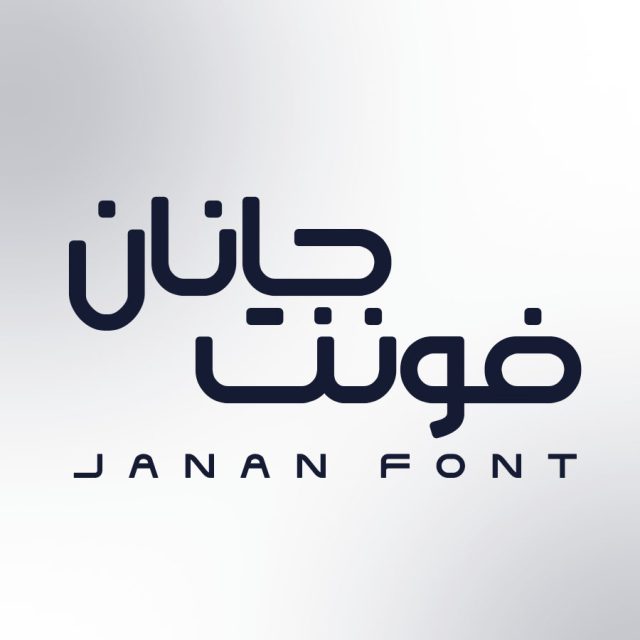
فونت فارسی جانان Janan Font
فونت حرفه ای جانان منتشر شد!
بهترین فونت برای طراحی لوگو و تولید محتوای فارسی
جانان مرکب از جان و آن ریشه در جان دارد… یک نفس بی یاد جانان برنمی آید مرا! فونت فانتزی جانان اثر جدید هاشم شهرزاد یک فونت مدرن و دارای طراحی زیباست. تایپ فیس جانان برای کلمات و عبارات کوتاه و بلند طراحی شده و بیشتر مناسب کاور و اسلاید شبکههای اجتماعی و تبلیغات و بسته بندی میباشد. از آنجایی که فونتهای فانتزی امروزه بسیار محبوب هستند، از فونت جانان میتوانید برای طراحی لوگوتایپ و موارد دیگر استفاده کنید.
فونت تایپوگرافی جانان
طراحی لوگو و تایپوگرافی با فونت
- طراحی بسته بندی و چاپ
- مناسب استفاده در تابلو ها
- مناسب استفاده در تبلیغات محیطی
- فونت برای طراحی لوگو
- مناسب تایپوگرافی در طرح های فارسی
- فونت مناسب طراحی وبسایت
- فونت مناسب تیتر ها و محتوا
- فونت خاص برای کاور پست اینستاگرام